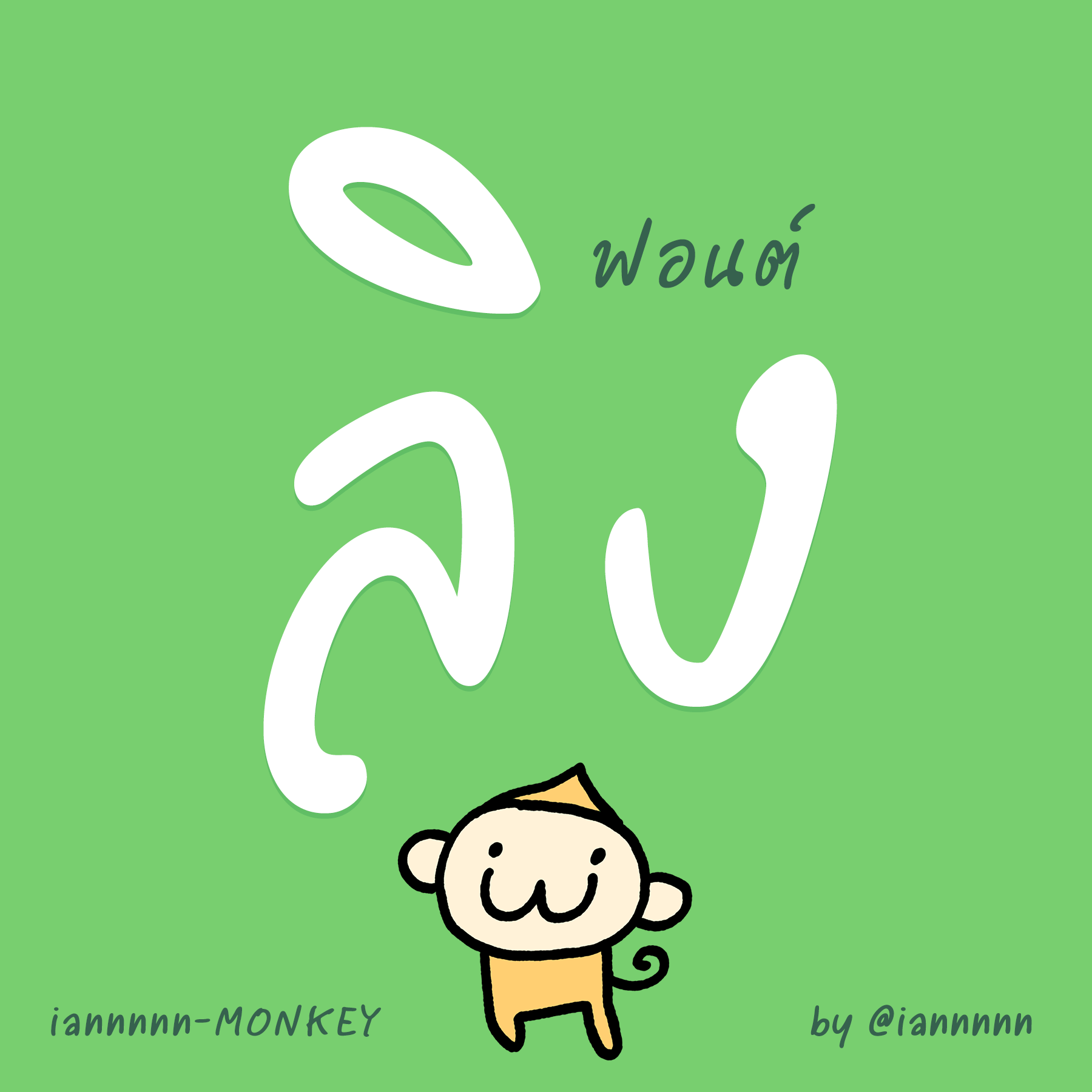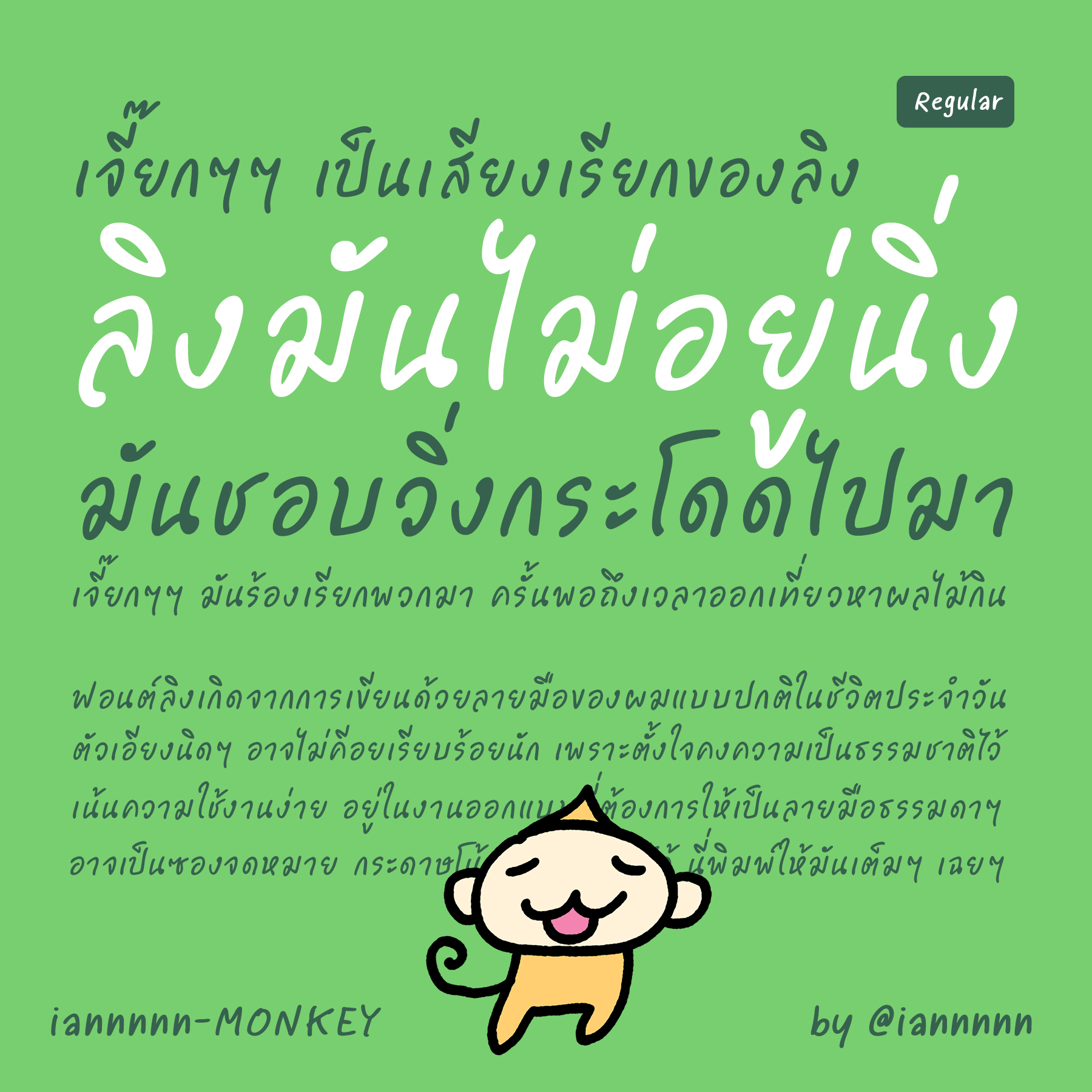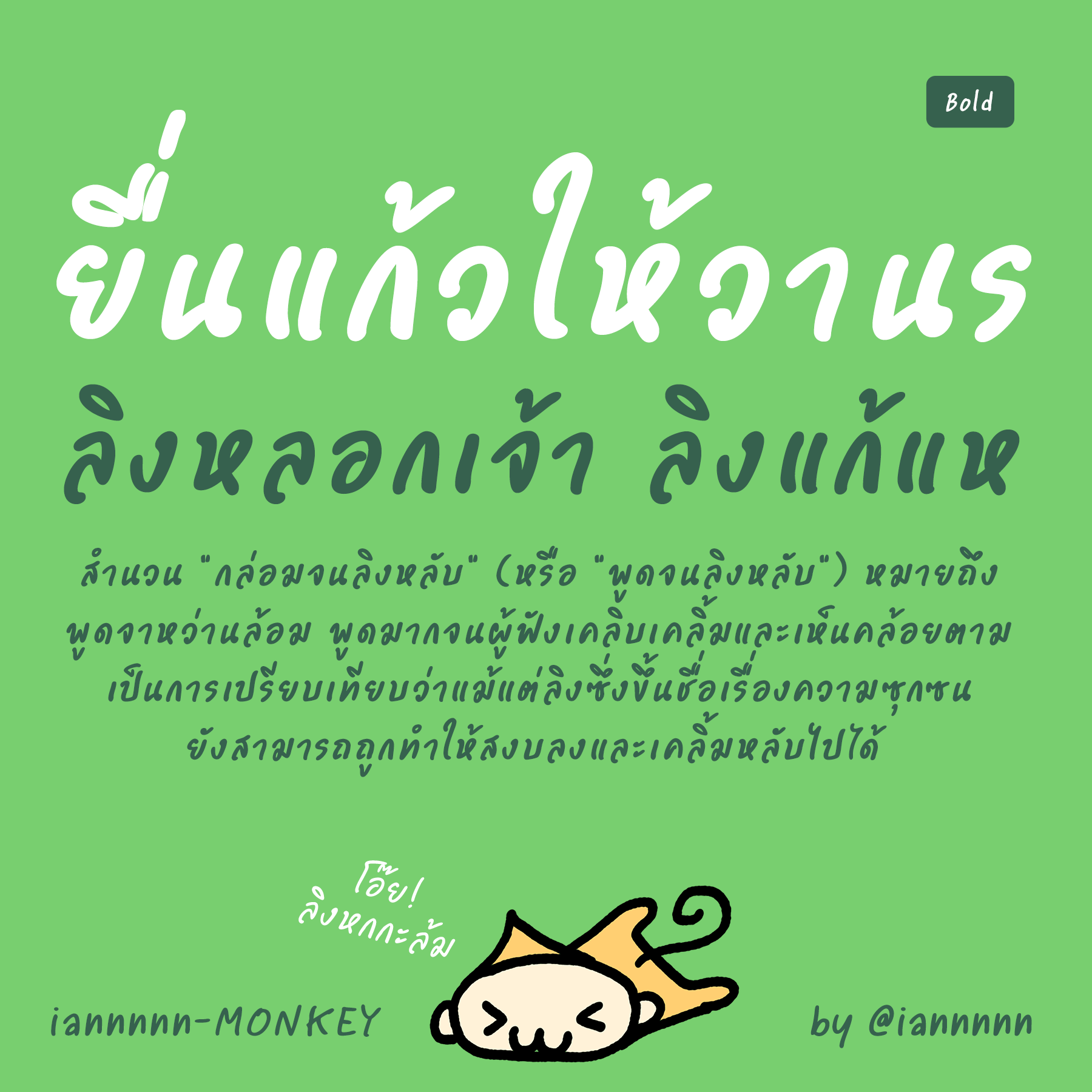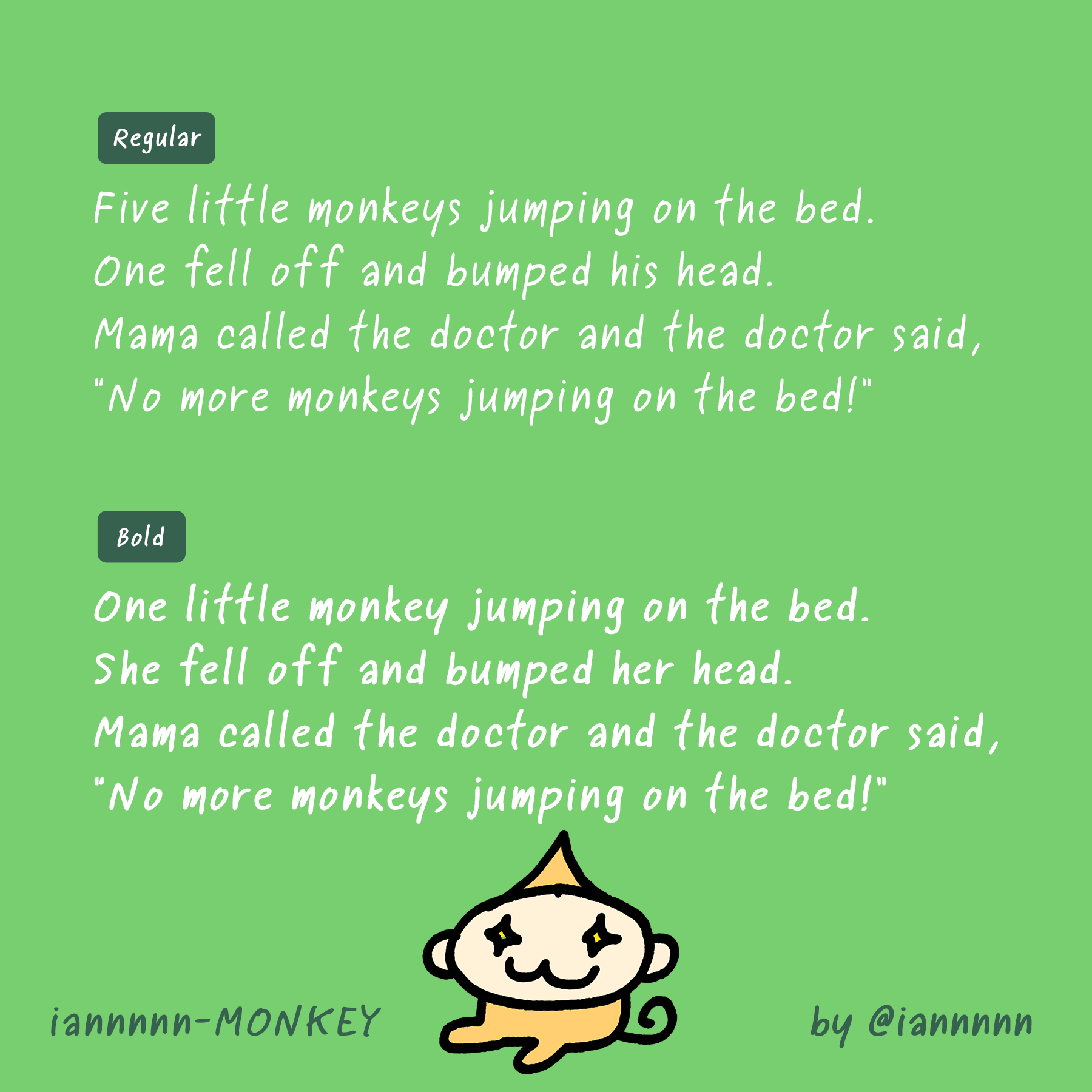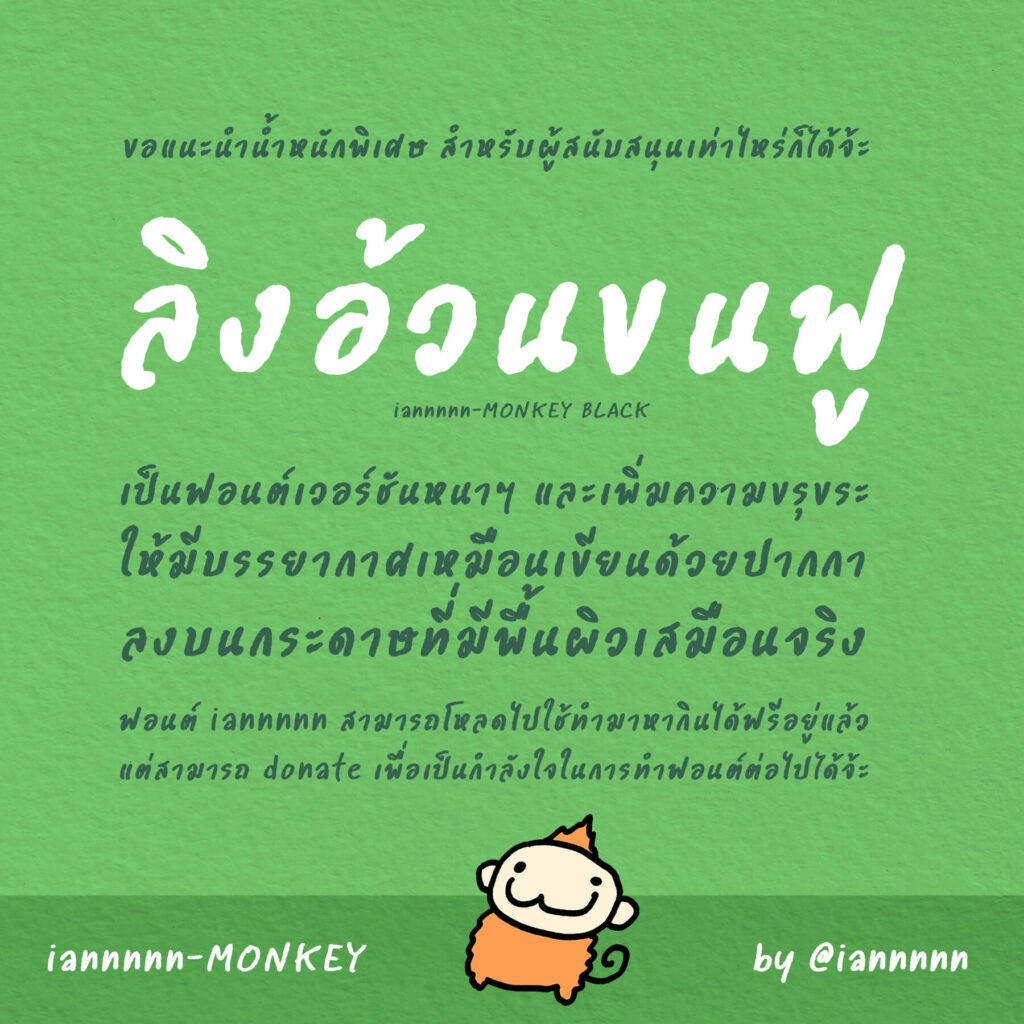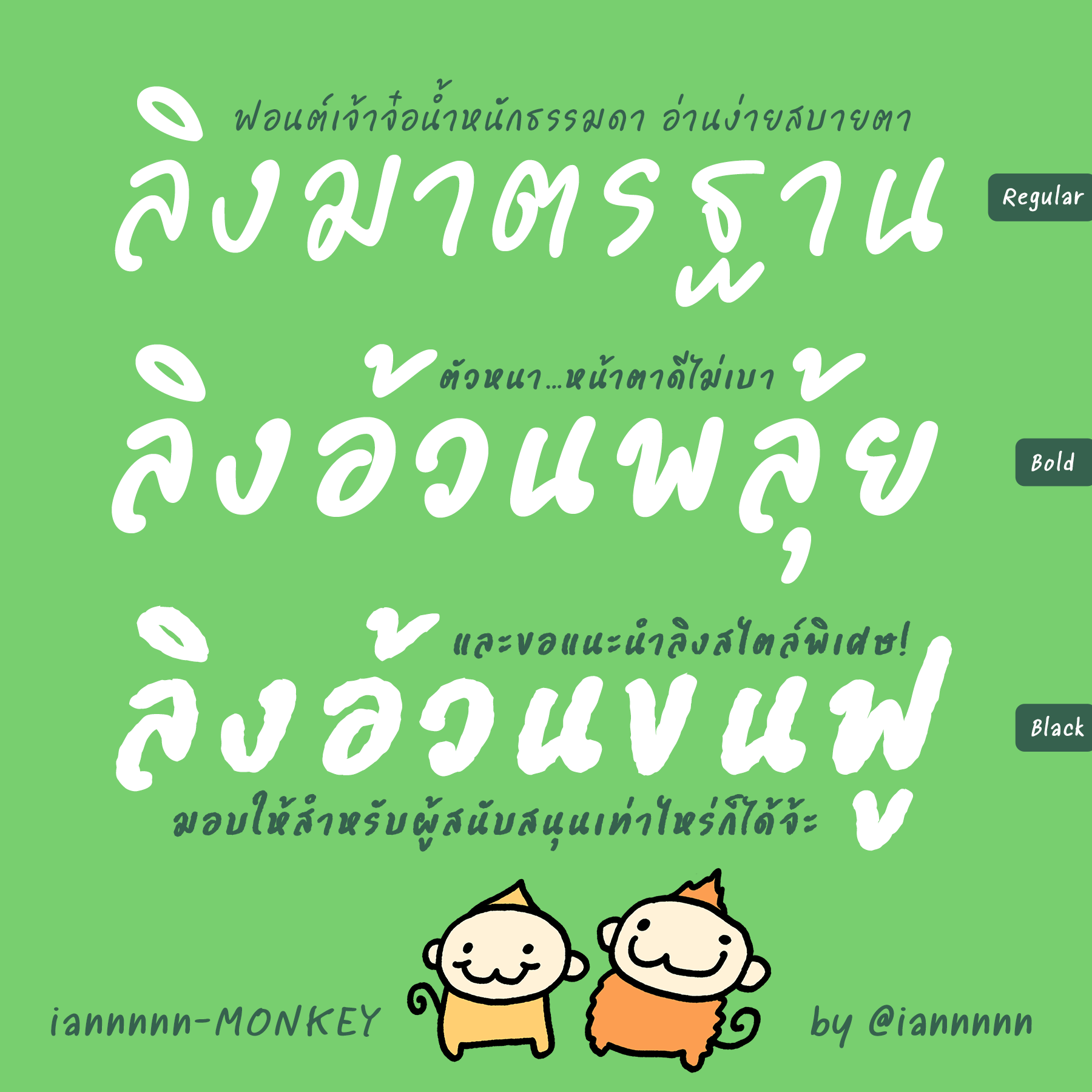
ลิง (iannnnn-MONKEY)
ฟอนต์ลายมือแบบธรรมชาติ เขียนหวัดๆ เร็วๆ แต่ยังอ่านง่าย ให้ความรู้สึกสบายๆ ตัวเอียงนิดๆ แจกฟรีทั้ง 2 น้ำหนัก (ลิงกลางและลิงหนา) พร้อมสไตล์พิเศษ ลิงอ้วนขนฟูสำหรับผู้ donate เท่าไหร่ก็ได้จ้า
อยากบันทึกลายมือของตัวเองในปัจจุบันไว้ว่ามีหน้าตาเป็นแบบนี้ ก็จะมีกลิ่นคล้ายๆ iannnnnBKK (2006) ในอดีต และฟอนต์เป็ด แต่อันนี้จะเป็นสไตล์ปากกาบรัชที่มีน้ำหนักในการกดนิดๆ แต่ไม่ contrast จัดนัก